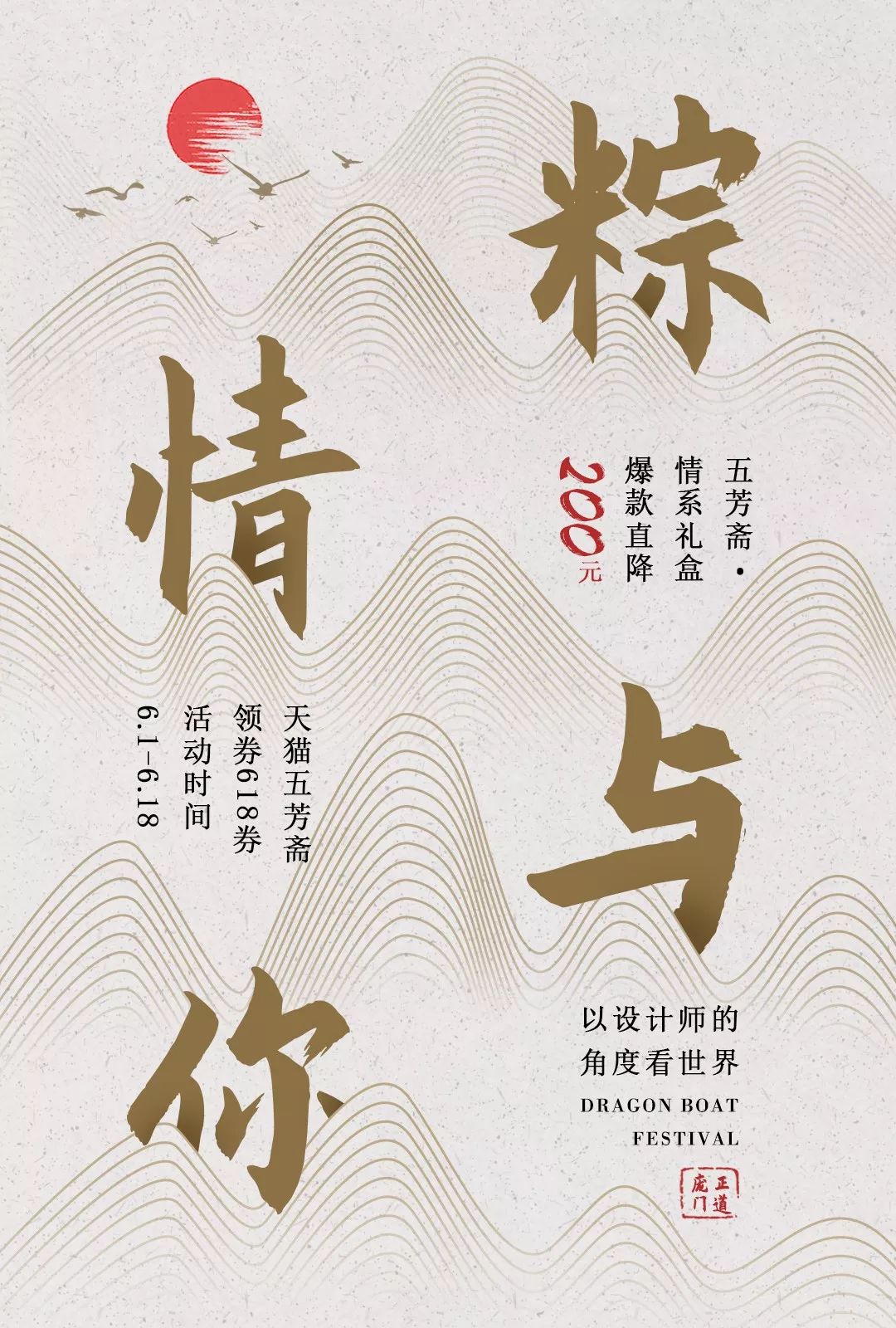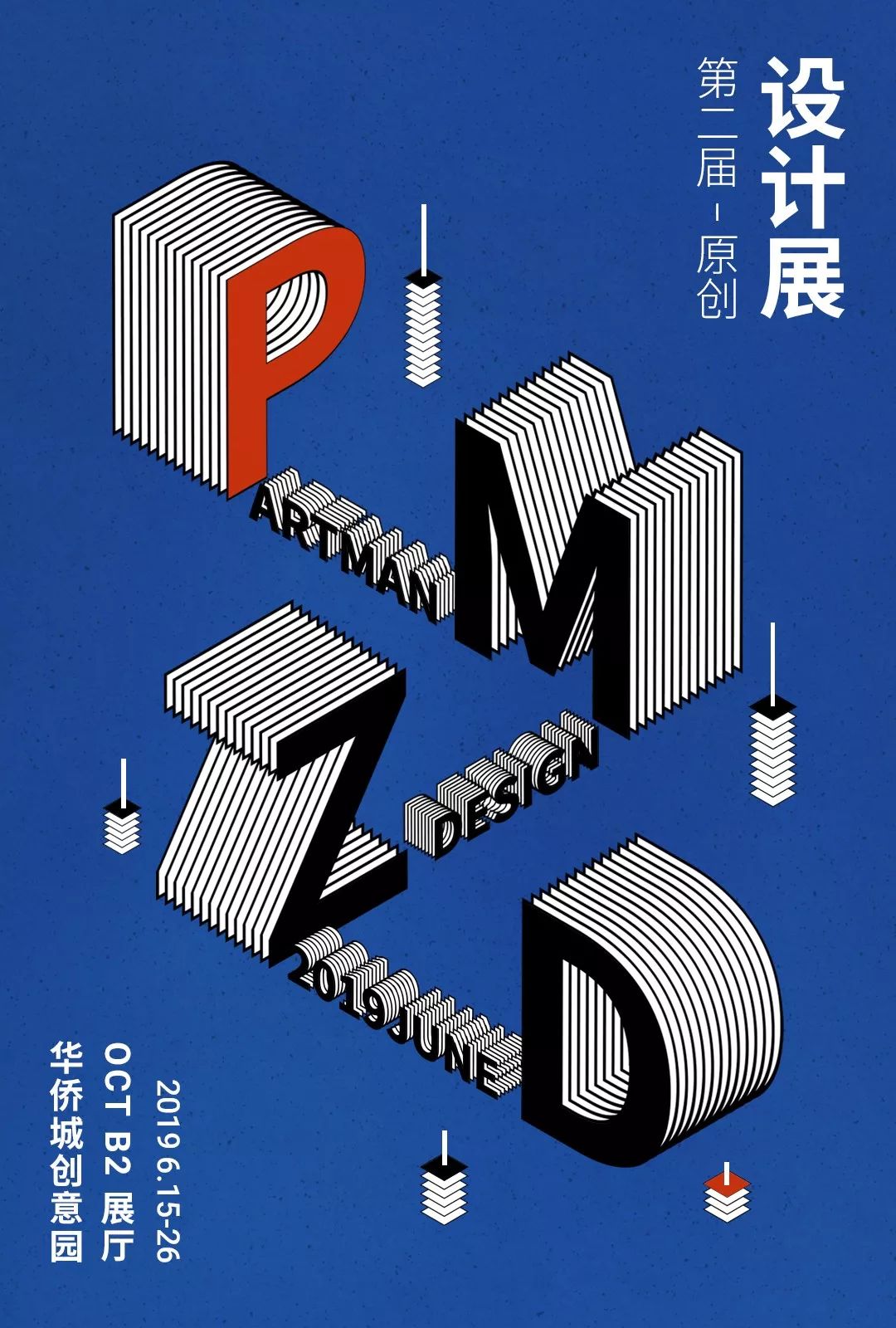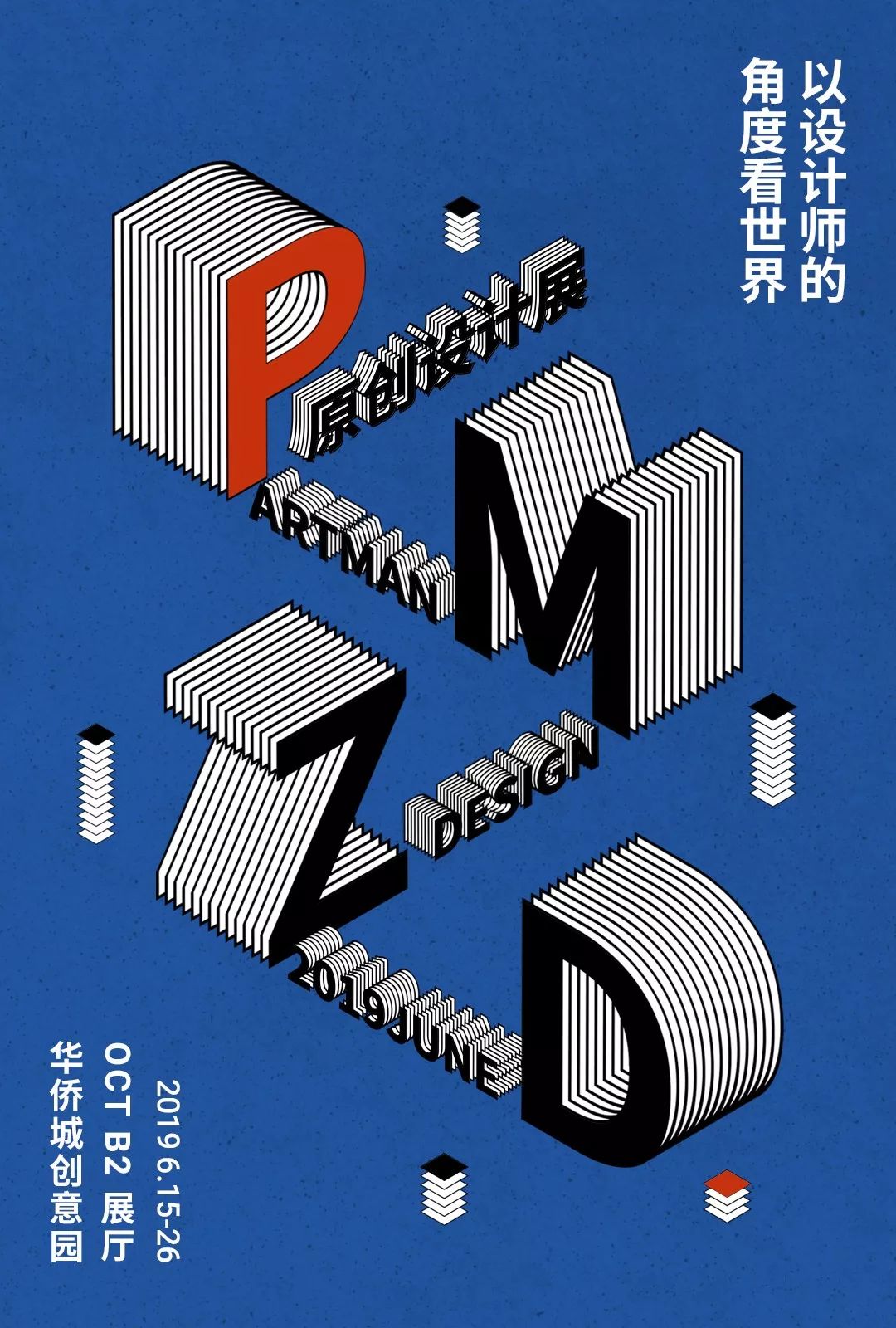
一篇文了解AI的混合工具(上)
今天分享AI里的混合工具给大家
你问有什么特别之处?
看下面用AI混合工具做两种样式
这山脉的线条用不好钢笔工具会画到哭吧
这些叠加字效果
用PS爸爸也不那么容易做啊
但是AI
可以让你一秒变有型!
先从基础学习怎么用AI里的混合工具
快捷键按W调出混合工具
单击工具栏混合工具图标
方法1:单击混合工具图标,按Enter回车键调出混合选项。
方法2:双击混合工具图标调出混合选项
方法3:选择菜单对象-混合-混合选项,弹出混合选项。
方法1:先设置好混合选项内容(混合选项内容下面会介绍)后,鼠标变成方块过渡的样式分别在两个图形上各单击一下完成。
方法2:框选中两个圆形执行快捷键,Ctrl+Alt+B混合效果完成。
方法3:框选中两个圆形执,行选择菜单对象-混合-建立,混合效果完成。
方法1:选择菜单对象-混合-释放
方法2:选中图形,执行快捷键Ctrl+Shift+Alt+B,取消混合效果。
敲黑板!!重点知识来了
开始两个案例效果都是通过
调整混合选项里实现的
下面来学习混合选项
当两个图形一样、颜色一样。过渡出来的形状和颜色和原图形一致。
当两个图形一样颜色不一样时呢?
用直接选择工具快捷键A,选中左侧图形更改颜色,当两个图形颜色不一样时就变成了两个颜色的渐变过渡。两个图形颜色相差越大混合渐变效果越明显。
还可以通过改变一端图形大小、图形形状做各种效果 。
选择指定步数调整数值,数值越大混合渐变的过渡的图形越多。
这是调整图形与图形直接的距离,数值越大混合渐变的图形距离越小。
是不是觉得炒鸡简单?
用混合工具做端午海报背景线条。首先在AI里用钢笔工具勾勒一条山脉的线条,并复制这条线选中两条路径。执行混合效果,在弹出混合选项里调整指定步数,重叠山脉效果完成了。
接着把AI里的线条导出PSD格式
在PS离打开,开始端午海报设计
看下完整版
下面一起来做叠加字海报吧
先在AI里用混合工具做好字的形
在导入PS里进行加工就完成啦